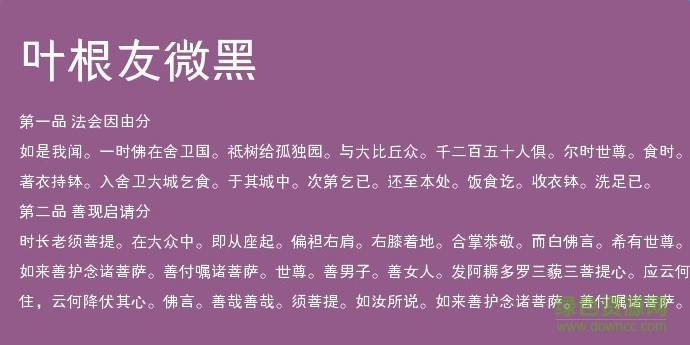
叶根友微黑简体是一款古典正规风格字体软件,微黑简体笔画工整非常鲜明醒目,字体所占空间非常一致,艺术气息十足,在海报广告标题有着不小的应用,还有更多好看字体欢迎来绿色资源网下载体验!
叶根友微黑简体是一款正规的黑体类型的印刷体,整个字体轻松活泼而有时代鲜明的特征,整个笔画横度微斜切,干净而大气,简约是这款字体的主要特色。每个笔画15度斜角的设计,使整个字型看起来更具时尚大气,在应用于内文、标题等都是不错的选择,叶根友微黑从设计到制作历时数年,工程量是普通手写字体的数倍,每个笔画和结构架次都需要经过精心布局,以求好的效果呈现给用户。
该字体笔画工整,一笔一画毫不拖泥带水,在一些正式文章的书写印刷方面得到广泛的应用,整体效果十分优美耐看,值得使用收藏!